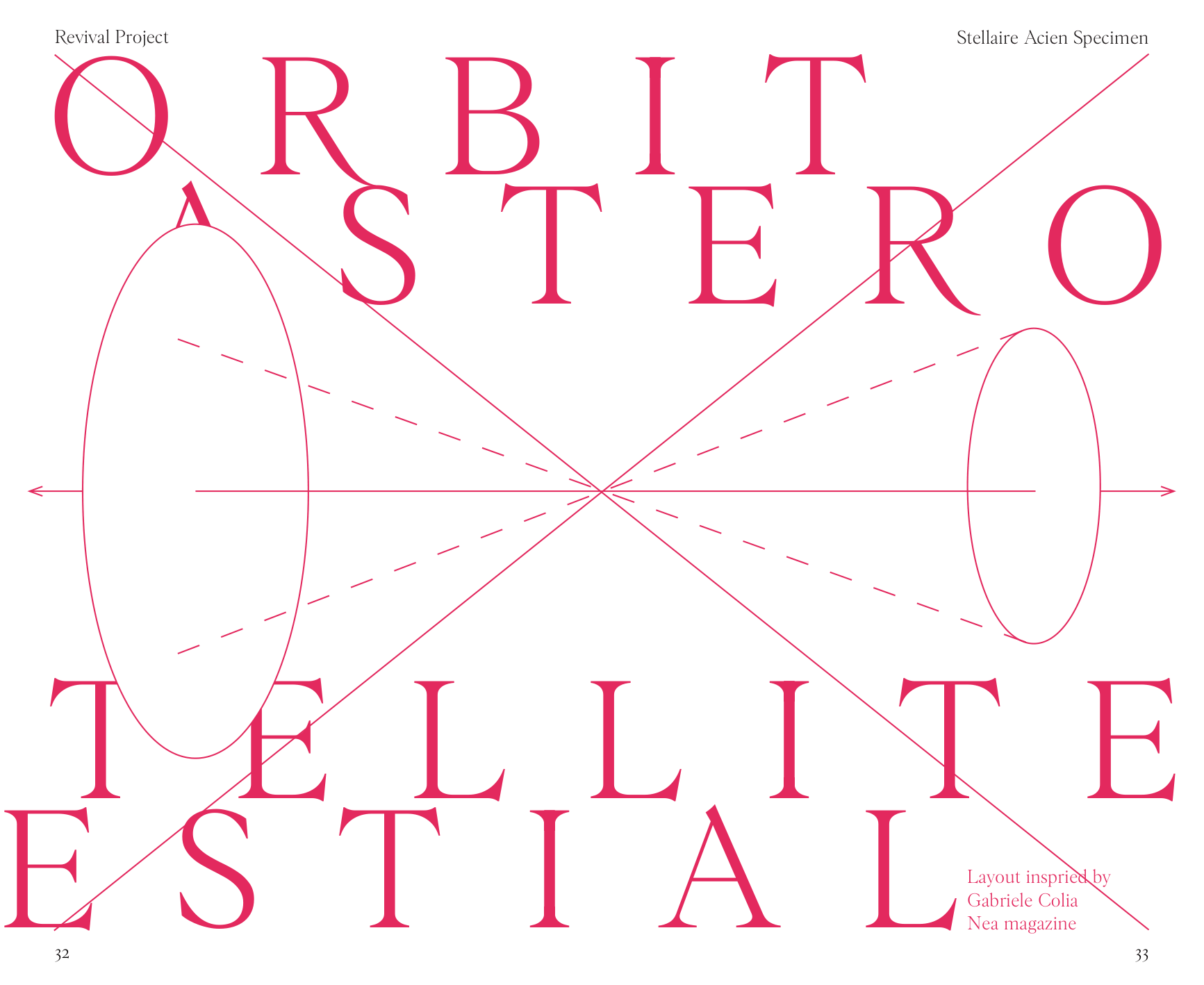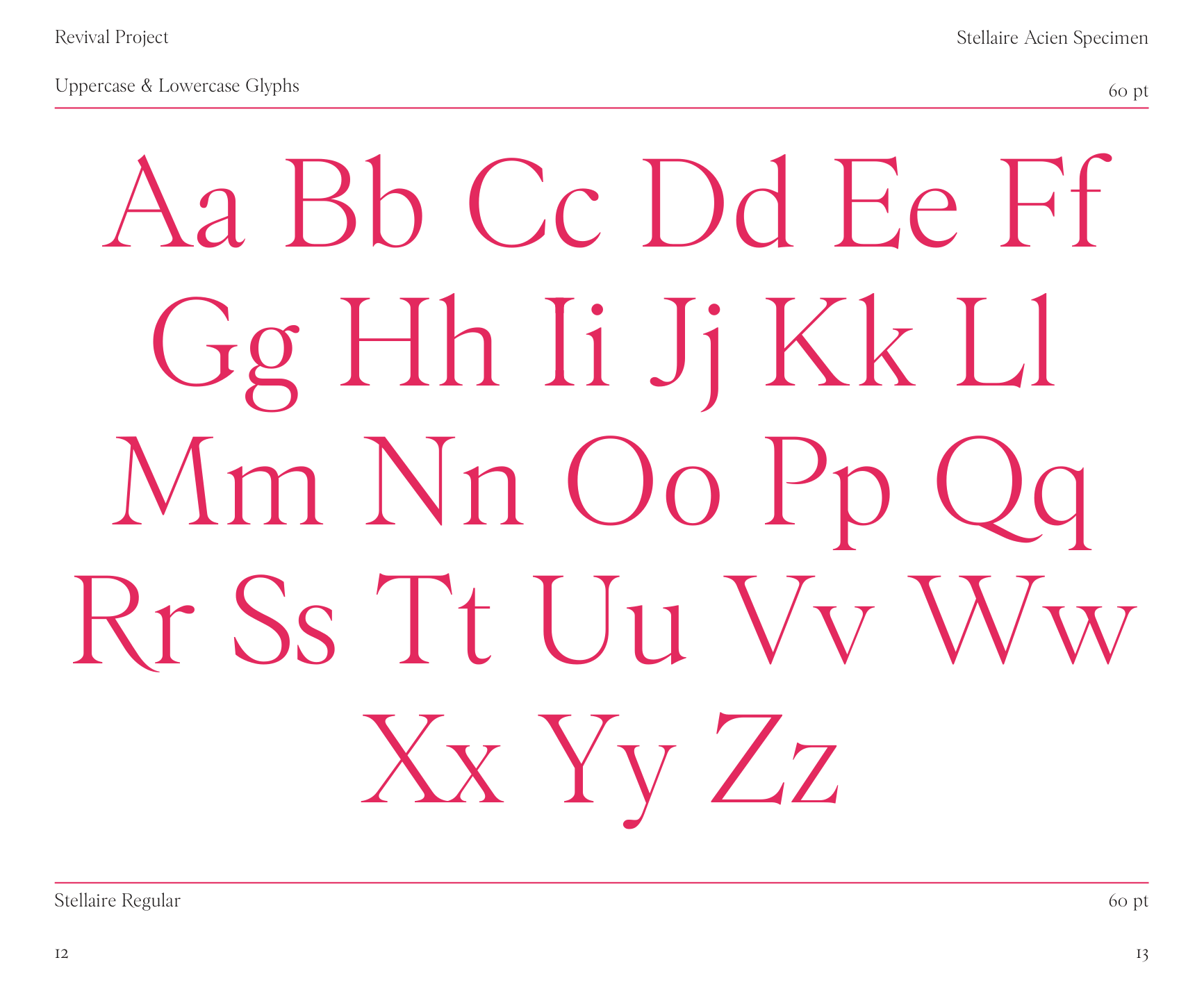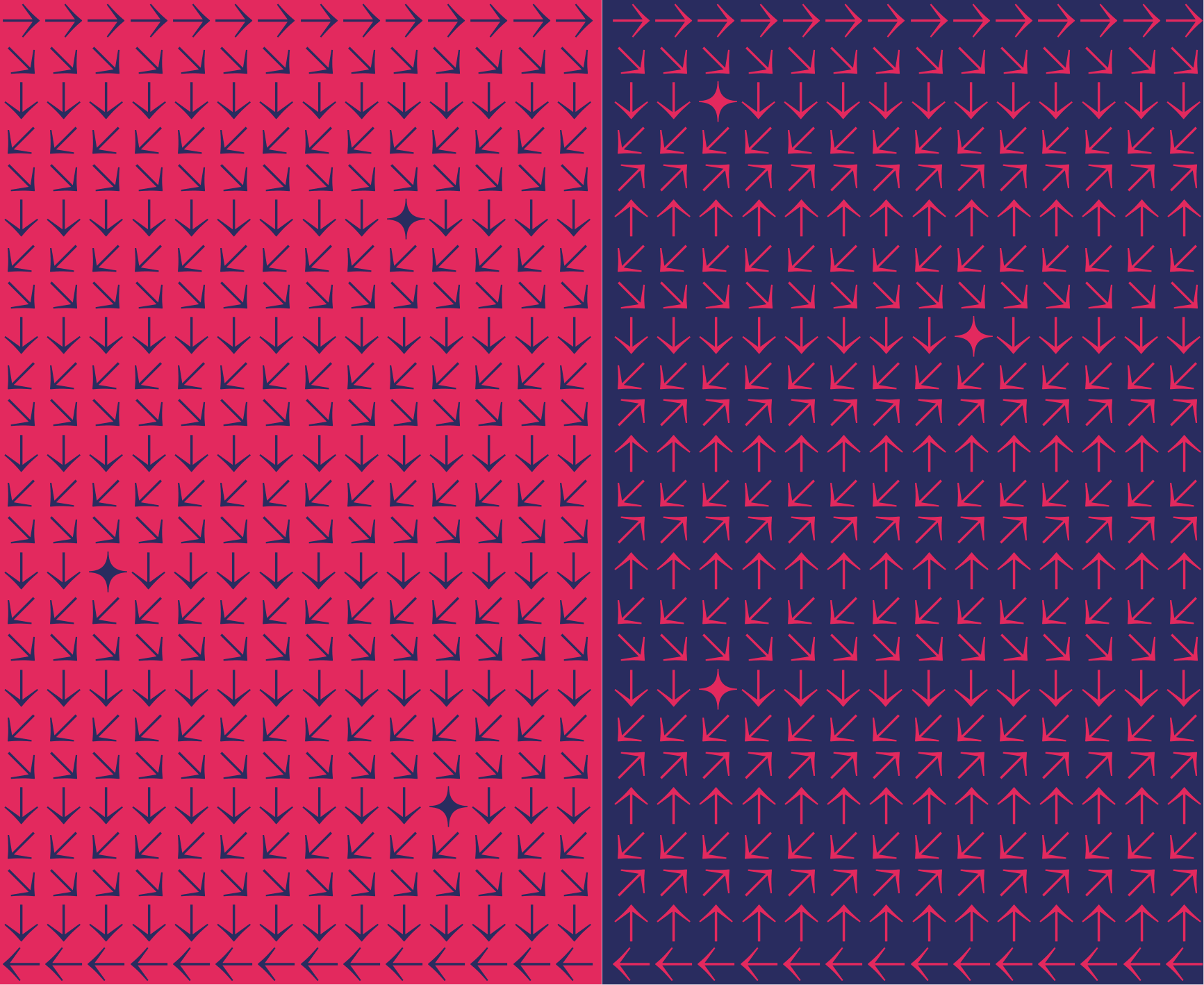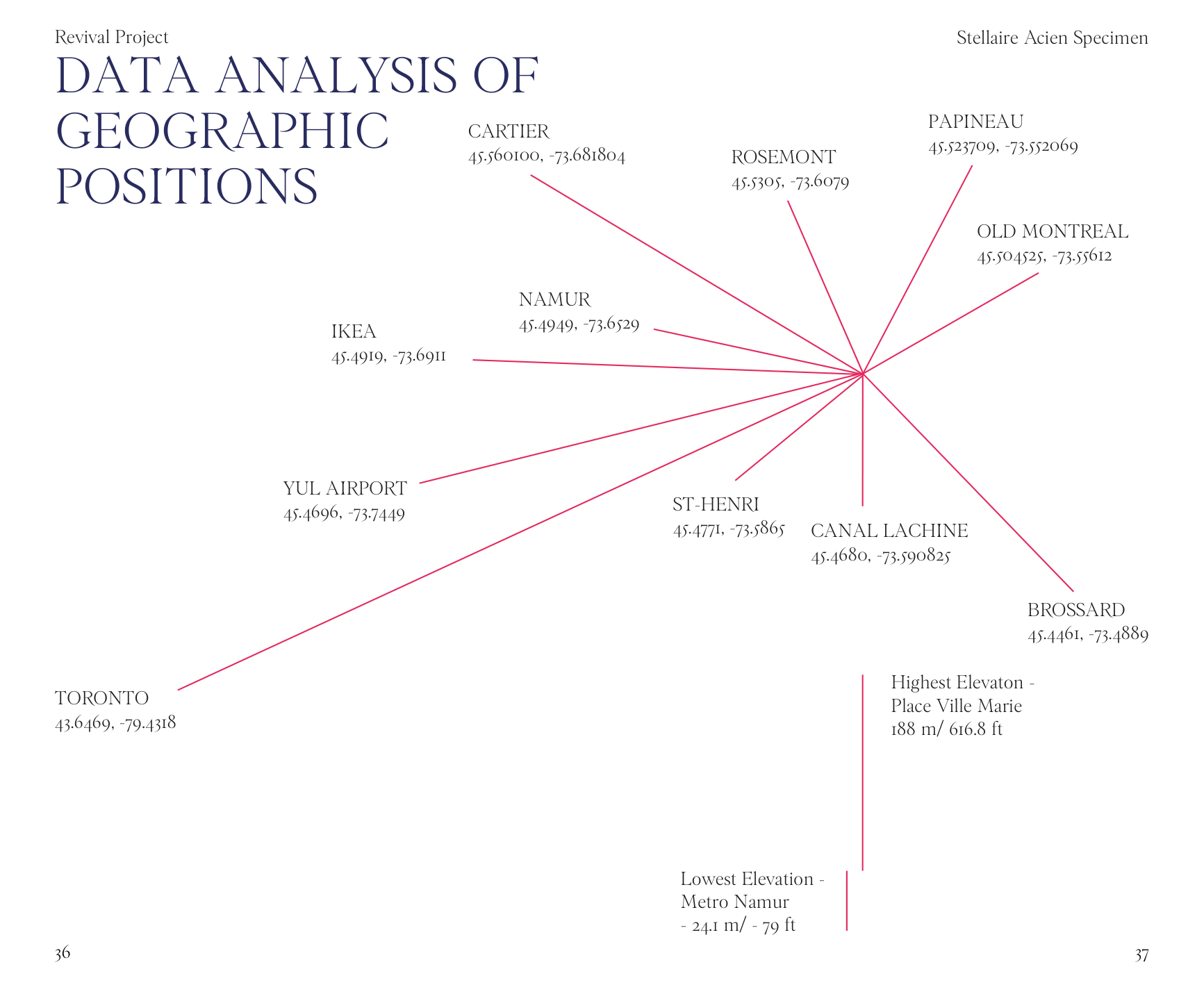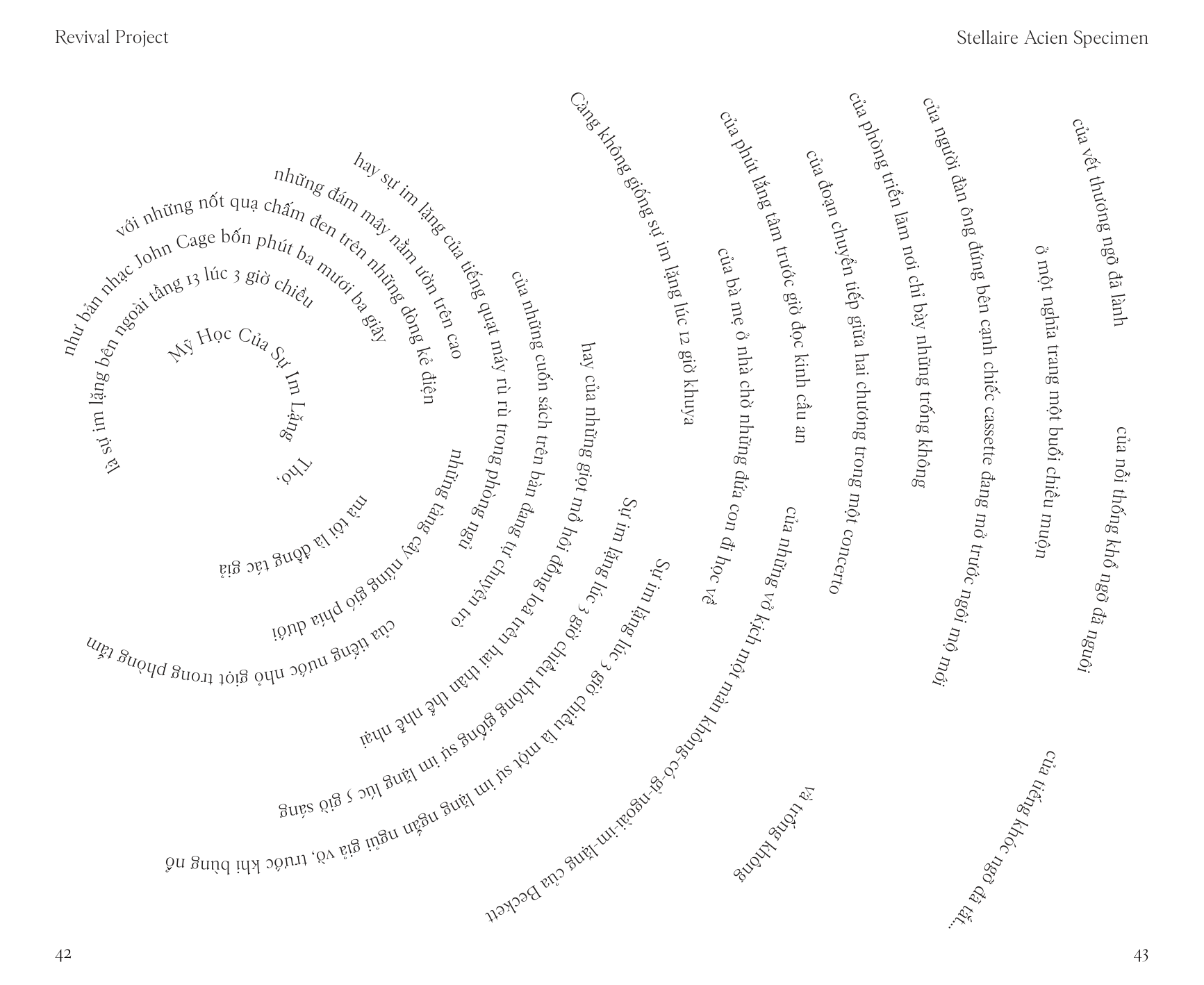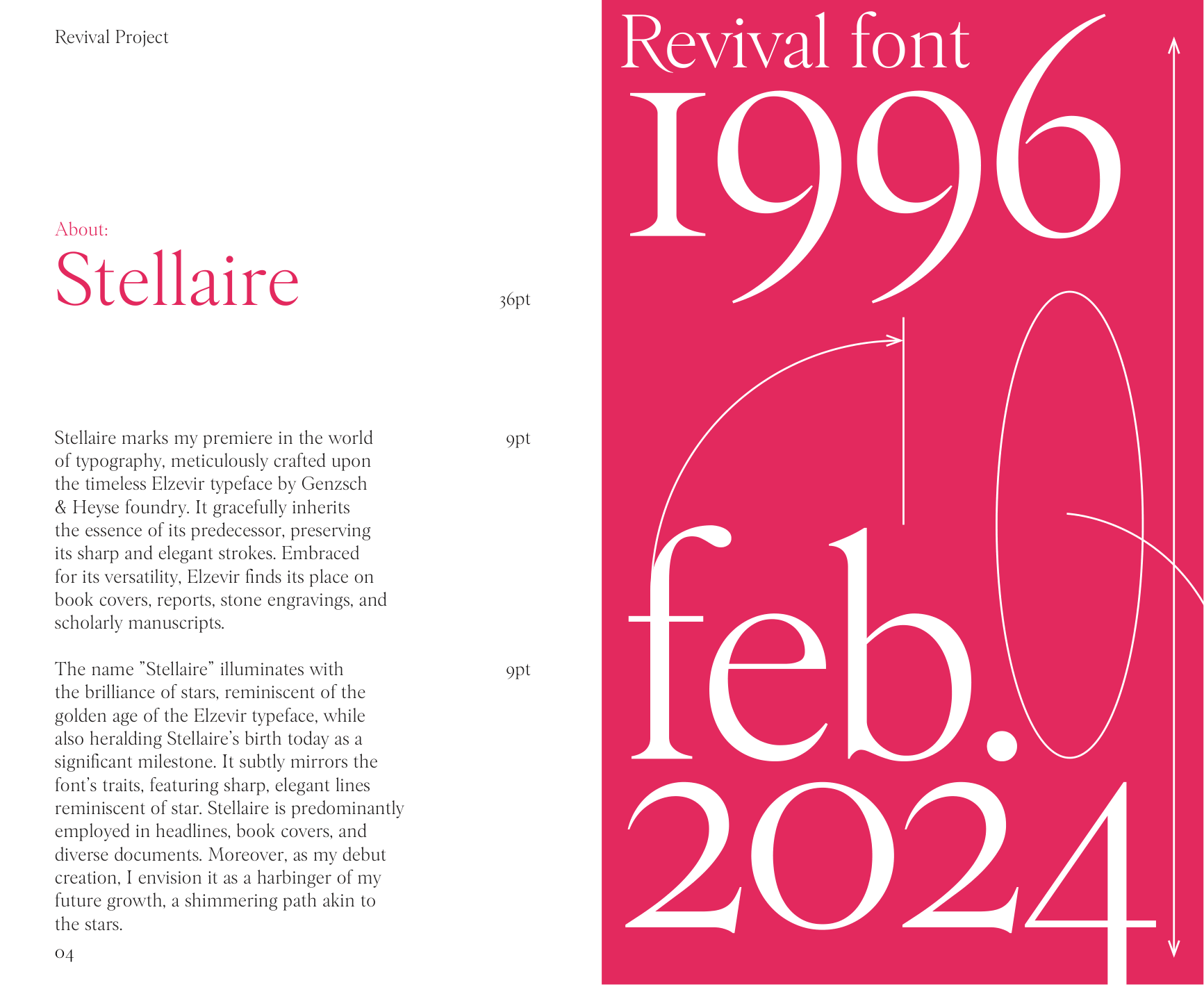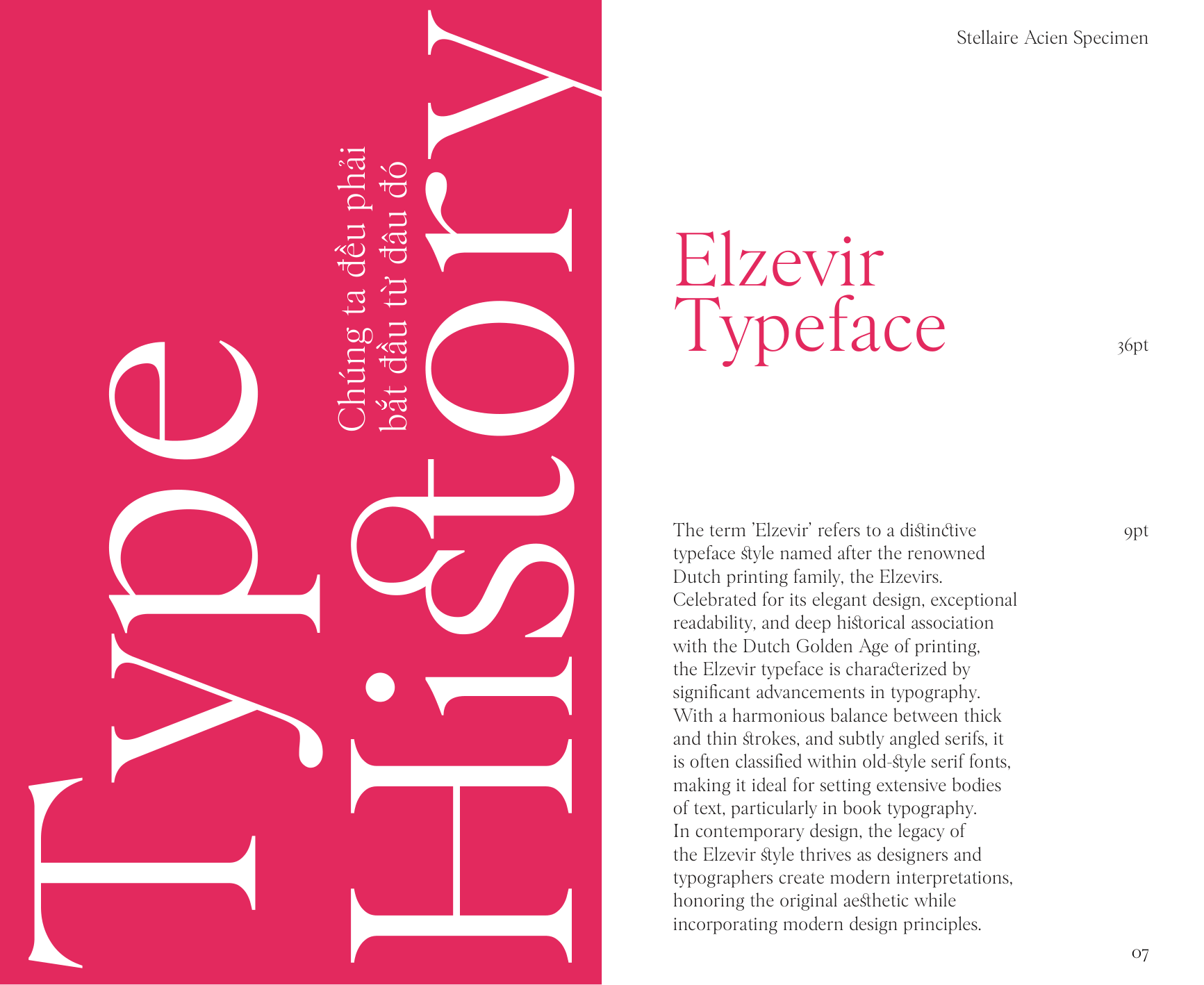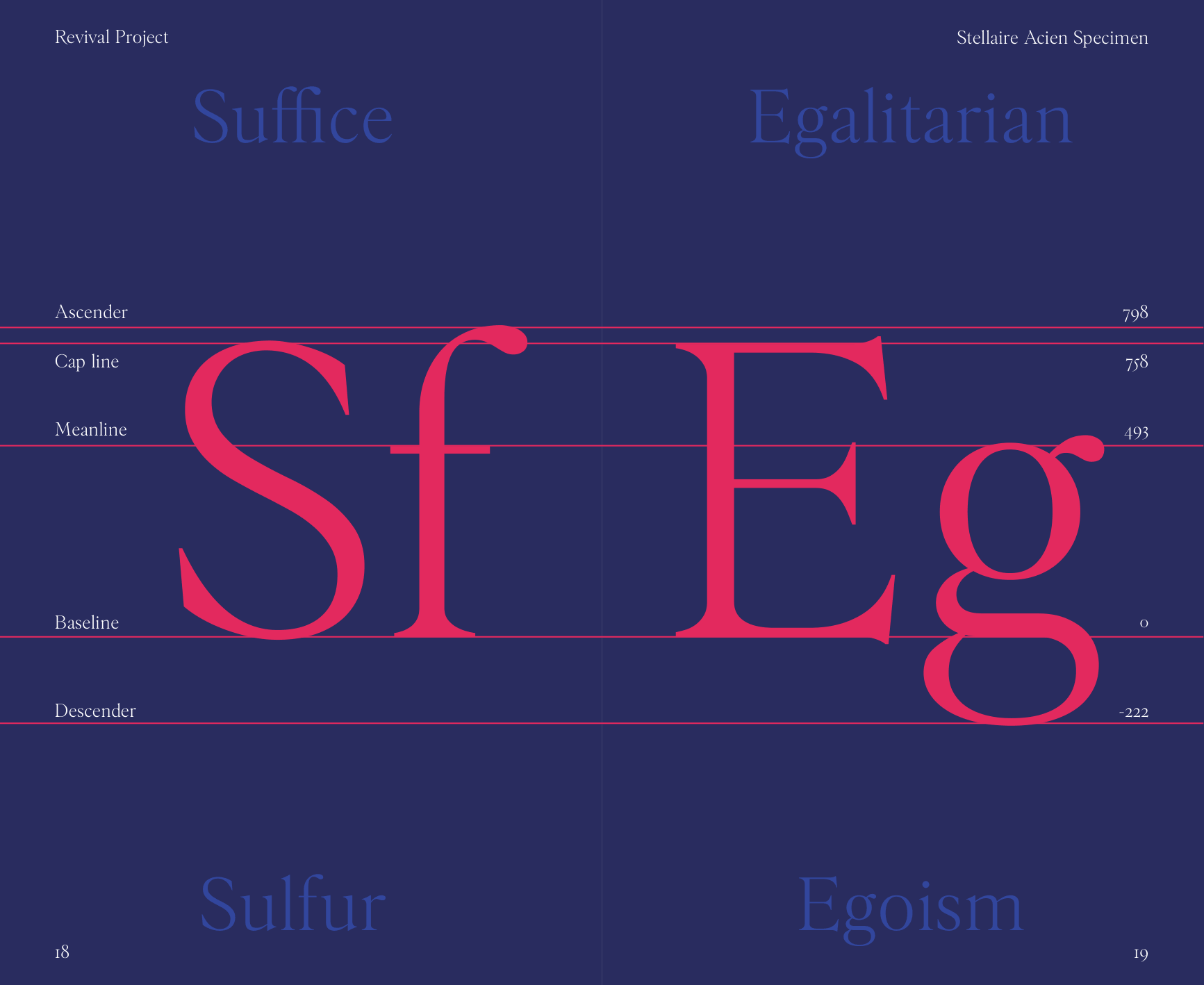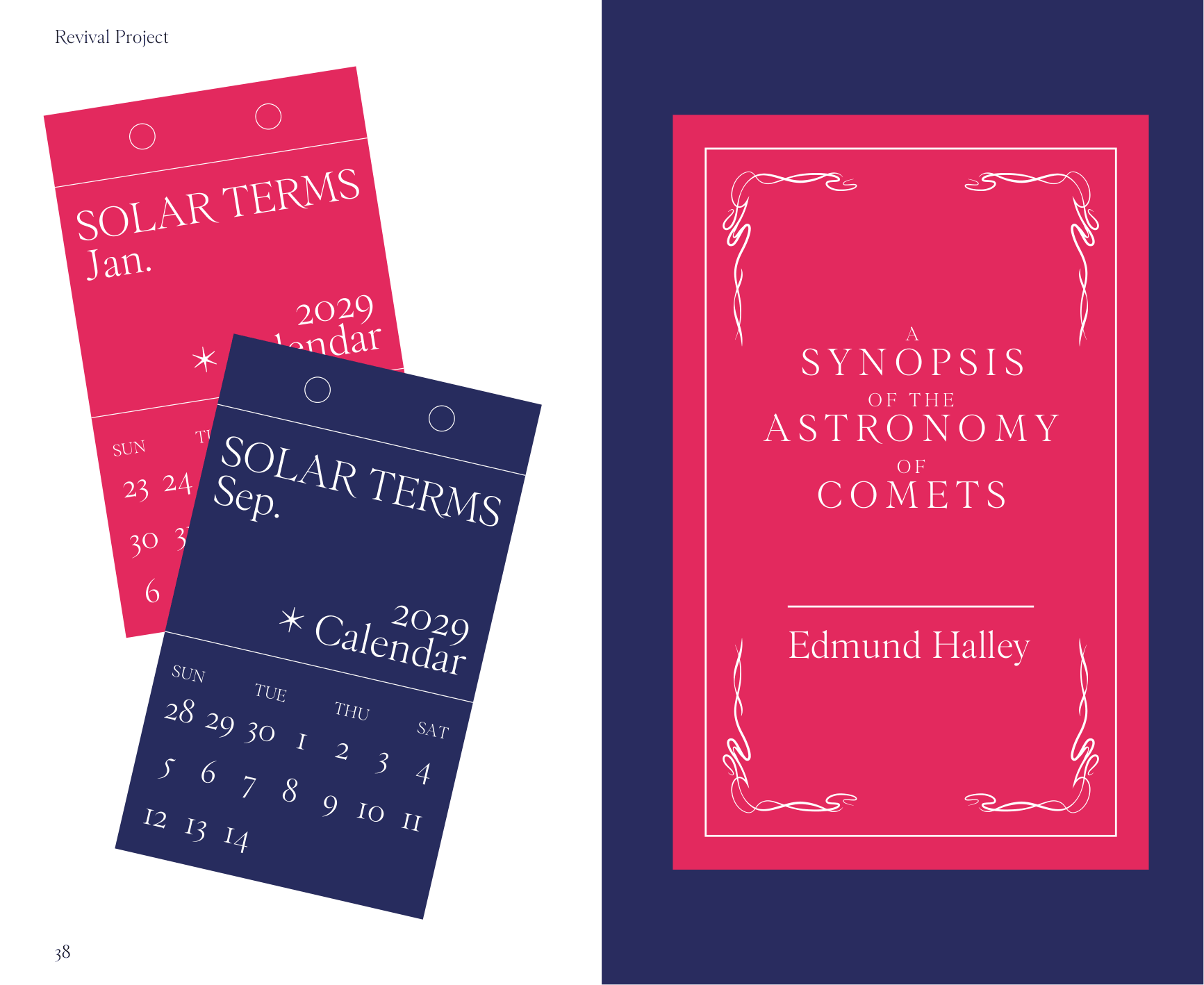
Stellaire
Về Stellaire: Phỏng lại Elzevir Ancien, Stellaire giữ lại tỷ lệ khá cao ráo và đạo mạo. Lướt khoan thai trên serif vuốt chéo xuống, Stellaire điềm nhiên phô diễn đức hạnh của mình trên trang giấy. Một số tạo hình như gai ở chữ G hay chân R và đuôi Q đẩy thêm nét yêu kiều cho phông chữ này.
Transitional Serif
Display
Stellaire
Scholarly
Stellaire
Intelligence
Stellaire
Ancien Replica
Stellaire
Embrace Versatility
Stellaire
The term Elzevir refers to a distinctive typeface style named after the renowned Dutch printing family, the Elzevirs.
Stellaire
Celebrated for its elegant design, exceptional readability, and deep historical association with the Dutch Golden Age of printing, the Elzevir typeface is characterized by significant advancements in typography. With a harmonious balance between thick and thin strokes, and subtly angled serifs, it is often classified within old- style serif fonts, making it ideal for setting extensive bodies of text, particularly in book typography. In contemporary design, the legacy of the Elzevir style thrives as designers and typographers create modern interpretations, honoring the original aesthetic while incorporating modern design principles.